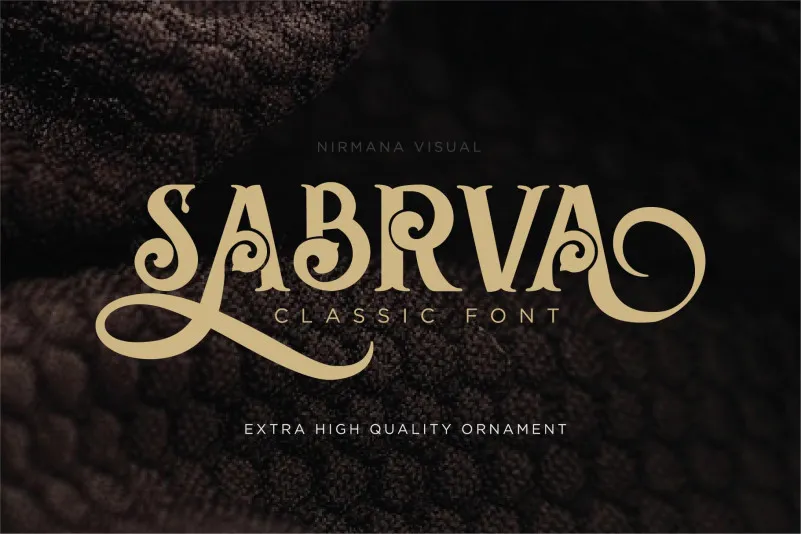
Sabrva é uma tipografia elegante criada pelo designer Nirmana Visual para ser usada tanto em composições complementares quanto como tipo forte que pode se sustentar sozinha. Sabrva oferece um toque de estilo clássico aos designs gráficos que a utilizam, proporcionando à sua tipografia uma personalidade única e sofisticada. Através da Sabrva, você pode explorar diferentes estilos clássicos e modernos ao mesmo tempo, dando ao seu design um toque de elegância sem se alongar demais na aplicação do estilo clássico. Combinar a Sabrva em projetos gráficos ou publicitários é uma maneira criativa de dar vida aos seus materiais, tornando-os ainda mais distintivos e sofisticados.